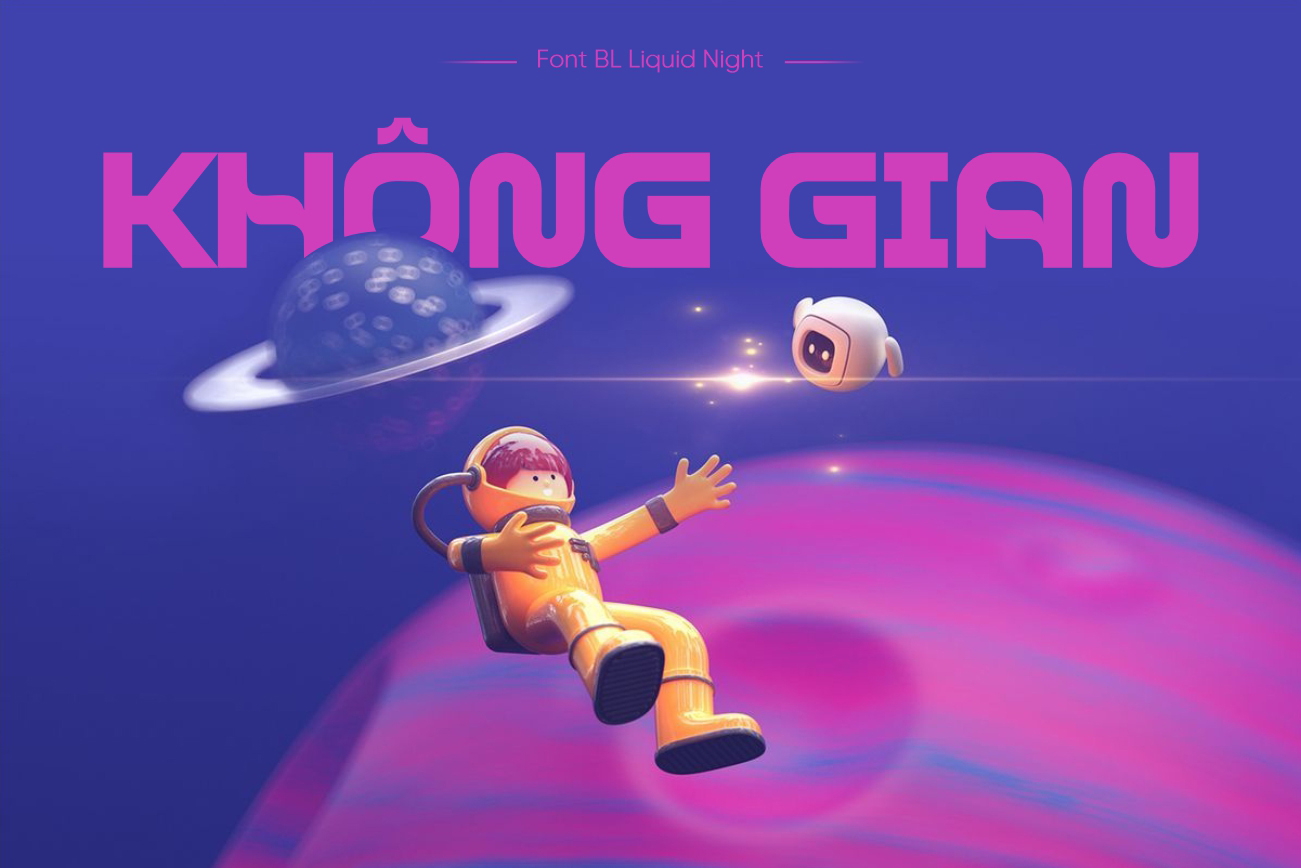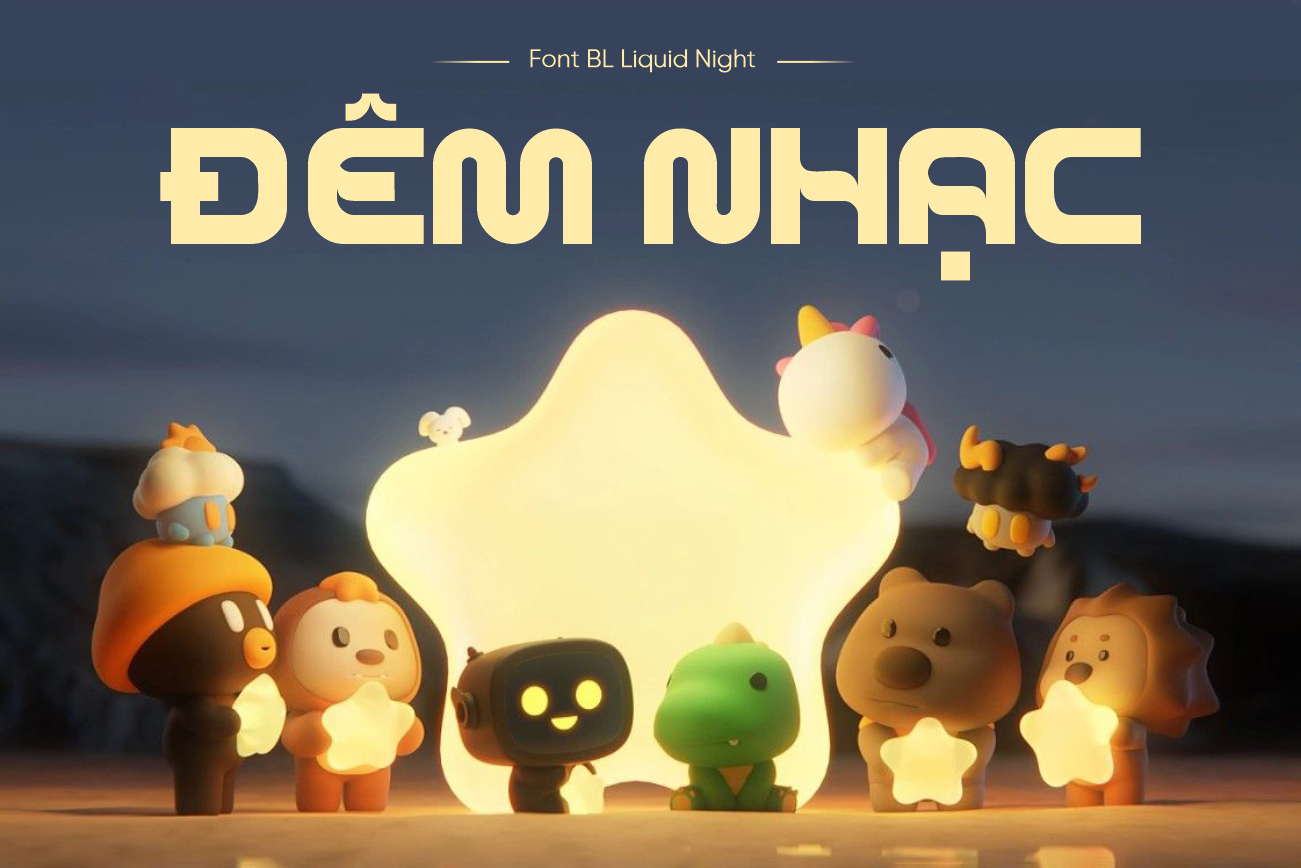
BL Liquid Night - Font công nghệ đầy cảm xúc thị giác
BL Liquid Night là phiên bản Việt hóa từ bộ font Liquid Night do Maikohatta thiết kế, mang tinh thần futuristic – techno – sci-fi rõ rệt và đầy cá tính thị giác. Lấy cảm hứng từ cảm giác “chất lỏng đêm tối”, bộ chữ tạo nên bầu không khí huyền bí, mạnh mẽ và tràn đầy năng lượng, rất phù hợp với những dự án muốn truyền tải tinh thần tương lai, công nghệ và hiện đại. Đây là một font chữ công nghệ mang tính biểu tượng thị giác cao, ngay khi xuất hiện đã có thể thu hút ánh nhìn nhờ độ dày mạnh mẽ, hiệu ứng thị giác cứng cáp và cảm giác kim loại – máy móc – cyberpunk cực kỳ ấn tượng.
Phiên bản Việt hóa BL Liquid Night được Team BL thực hiện tỉ mỉ giúp font hiển thị tiếng Việt đầy đủ dấu, sắc nét, giữ trọn linh hồn thiết kế gốc nhưng phù hợp hơn với nhu cầu sử dụng trong thiết kế tại Việt Nam.
Về kiểu dáng, BL Liquid Night sở hữu nét chữ vuông – góc cạnh, cấu trúc mạnh mẽ tạo nên cảm giác kiên cố như những khối công nghiệp vững chắc trong thế giới công nghệ tương lai. Các đường nét sắc nét, dày dặn, bố cục chữ cân bằng và hình khối chắc chắn giúp font trở nên cực kỳ nổi bật khi sử dụng cho tiêu đề lớn, banner, poster, logo hay bất kỳ thiết kế nào cần tạo điểm nhấn rõ rệt. Không dành cho văn bản dài, bộ font này được tạo ra với mục đích làm nổi bật thông điệp ngắn gọn, truyền tải cảm xúc mạnh mẽ và tạo hiệu ứng thị giác bùng nổ ngay lập tức. Chính vì vậy, BL Liquid Night thực sự thích hợp cho các bố cục đậm tính đồ hoạ, đặc biệt trong lĩnh vực game, công nghệ, âm nhạc điện tử, thiết kế sự kiện, quảng cáo hiện đại hay các dự án sáng tạo cần chất “ngầu”, khác biệt và cá tính.
Nguồn gốc của Liquid Night xuất phát từ tinh thần sci-fi kết hợp cảm giác cyberpunk đầy chất điện tử và chuyển động mạnh, vì thế khi trở thành BL Liquid Night, bộ font tiếp tục phát huy được trọn vẹn thế mạnh của mình trong môi trường sáng tạo Việt Nam. Đây là lựa chọn hoàn hảo cho những ai đang tìm một font chữ công nghệ táo bạo, sở hữu nét chữ vuông – góc cạnh, cấu trúc mạnh mẽ nhưng vẫn có sự mượt mà của dòng chất lỏng chuyển động trong bóng tối. BL Liquid Night không chỉ là một bộ font, mà còn là công cụ giúp tăng độ kịch tính thị giác, nâng tầm phong cách thiết kế và tạo dấu ấn rõ ràng cho bất kỳ dự án nào cần sự nổi bật, mạnh mẽ và đậm chất tương lai.